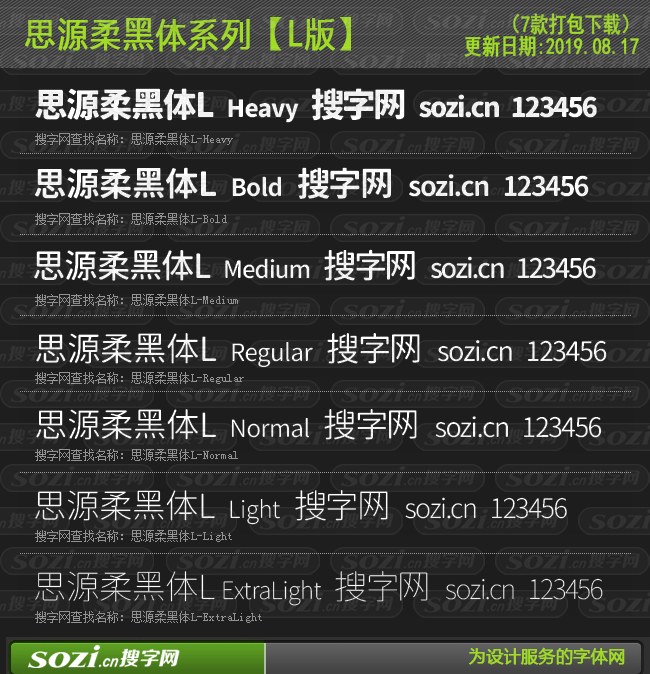
思源柔黑體系列【L版】
搜字網(wǎng)為大家提供思源柔黑體【L版】字體打包下載。思源柔黑體字體是基于思源黑體修改而成的,作者是日本的自家製フォント工房。 思源柔黑體是一種風格相對現(xiàn)代化的字體,這種字體筆觸簡單、質(zhì)量一致。在文字邊角以圓邊進行處理,似黑似圓,介于二者之間,而L系列的圓角最小 (最尖)。